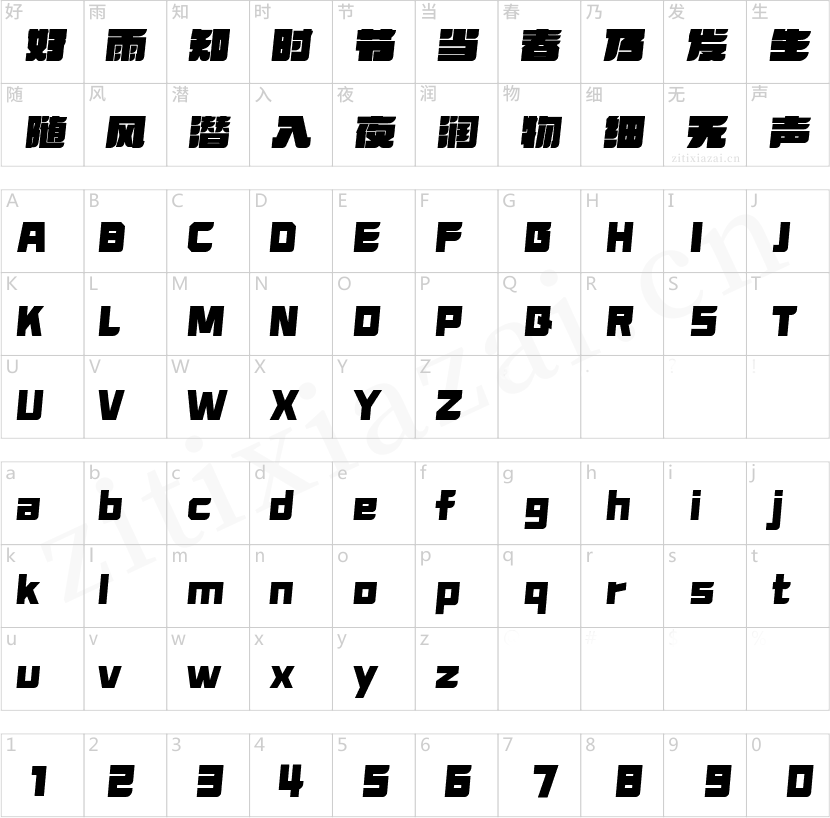
字魂奇迹宇宙体
字魂奇迹宇宙体,这款字体结构工整、笔画清晰,兼顾美观与易读性,适用于标题、正文、海报、包装、LOGO 等多种场景。字形优雅稳定,风格百搭耐看,适配日常排版与创意设计,让文字呈现更舒适、更具质感。字魂奇迹宇宙体一笔一画,皆是细节,以均衡的比例、流畅的线条打造舒适视觉体验,字形端正大气,风格简约现代。无论是商业设计、品牌宣传还是日常排版,都能轻松驾驭,让文字更有格调与力量。字魂奇迹宇宙体字体下载。
字魂字体字魂奇迹宇宙体字体是由字魂创意字库设计并生产的一款可商用的字体,被收录于字魂先锋系列。该字体支持GB-2312标准,包含6941个中文、字母、符号和数字,字体类型偏向黑体,具有力量、时尚的风格,在市面上广泛用于视频影视、视频综艺、企业文化等场景。